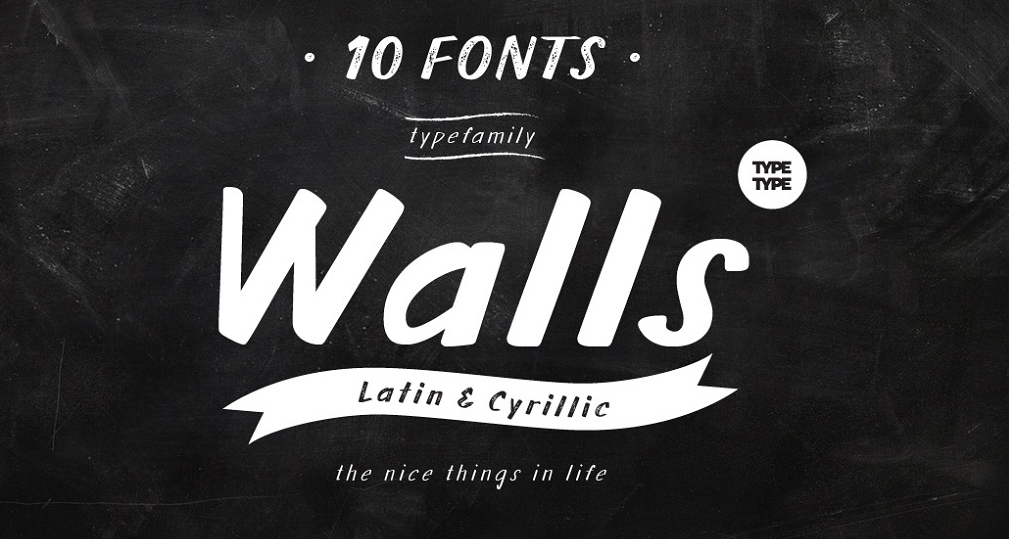
A TT Walls Font Family é uma criação profissional e moderna do designer Hamilton para a Typetype. Esta família de fuentes gerafose é perfeita tanto para aqueles que buscam um estilo contemporâneo quanto para aqueles que desejam incorporar elementos sustentáveis em seus projetos. TT Walls foi pensado para permitir a combinação perfeita entre uma estética moderna e uma abordagem mais ecologicamente consciente. Esta fonte gerafose é uma excelente escolha para quem procura um estilo inovador que pode ser usado em uma ampla variedade de aplicações, como logotipos, headlines e pequenos títulos. Suportando mais de 70 idiomas, a TT Walls Family oferece uma ampla gama de opções de tipografia para atender às necessidades de diferentes culturas. Além disso, compreende um total de dez tipos em cinco pesos populares (Suave, Leve, Regular, Negrito e Escuro), permitindo que os designers criem textos com o contraste necessário. A TT Walls Family é a escolha perfeita para aqueles que desejam adicionar um toque moderno e sustentável a seus projetos de design gráfico.